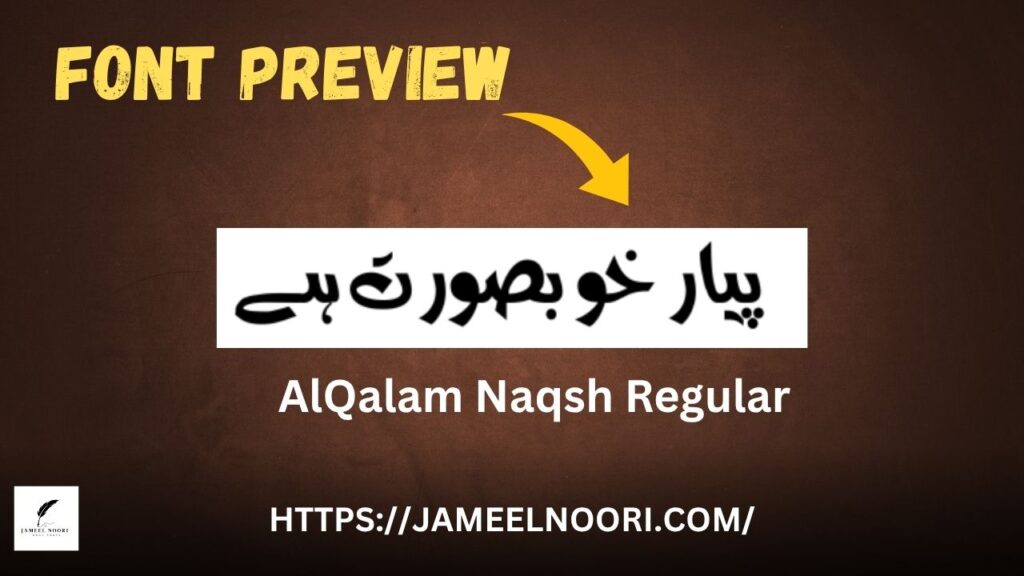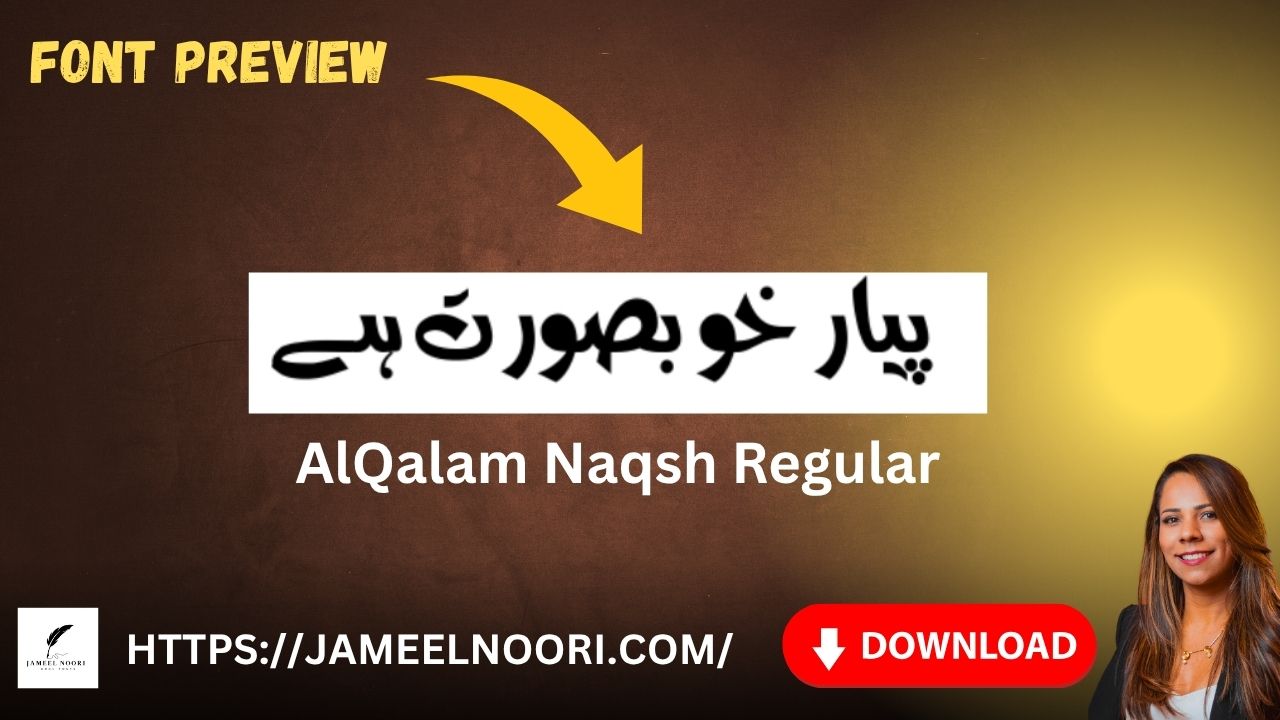
Introduction to AlQalam Naqsh Regular Font
Agar aap Urdu calligraphy, designing ya official documents banane ka shoq rakhte hain, to urdu font AlQalam Naqsh Regular font aap ke liye ek lajawab choice ho sakta hai. Ye font Urdu likhne walon ke darmiyan kafi popular hai aur is ka use aaj kal kai government documents, Urdu novels, and even educational materials mein ho raha hai.
Why Choose AlQalam Naqsh Regular Urdu Font?
✅ Easy to Read
Is font ki readability bohot achi hai jo ise printing aur digital use dono ke liye best banata hai.
✅ Professional Appearance
Ye font traditional yet elegant Urdu script ko modern look deta hai, jo isay presentations, books, and even official use ke liye perfect choice banata hai.
AlQalam Naqsh Regular Font Ki Features (Bullet Format)
- Classic Urdu Naskh style
- Best for Urdu content creators, bloggers, and students
Where You Can Use This Font
📌 Government Documents
📌 Urdu Poetry Designs
📌 Naat Books Layout
📌 Quranic Education Materials
📌 Social Media Urdu Graphics
📌 School Notes and Educational Projects
1. AlQalam Naqsh Regular font kis tarah ka font hai?
Yeh ek Regular Urdu TrueType font hai jo readability aur style dono mein best hai.
9. AlQalam Naqsh aur Jameel Noori Nastaleeq mein kya farq hai?
AlQalam Naqsh thoda straight aur readable font hai jabke Jameel Noori Nastaleeq ek decorative Nastaleeq font hai.
Agar aap ek stylish, readable, aur traditional Urdu font talash kar rahe hain, to AlQalam Naqsh Regular aap ke liye perfect choice hai. Is font ka professional look aur easy compatibility ise Urdu content creators ke liye best banata hai.